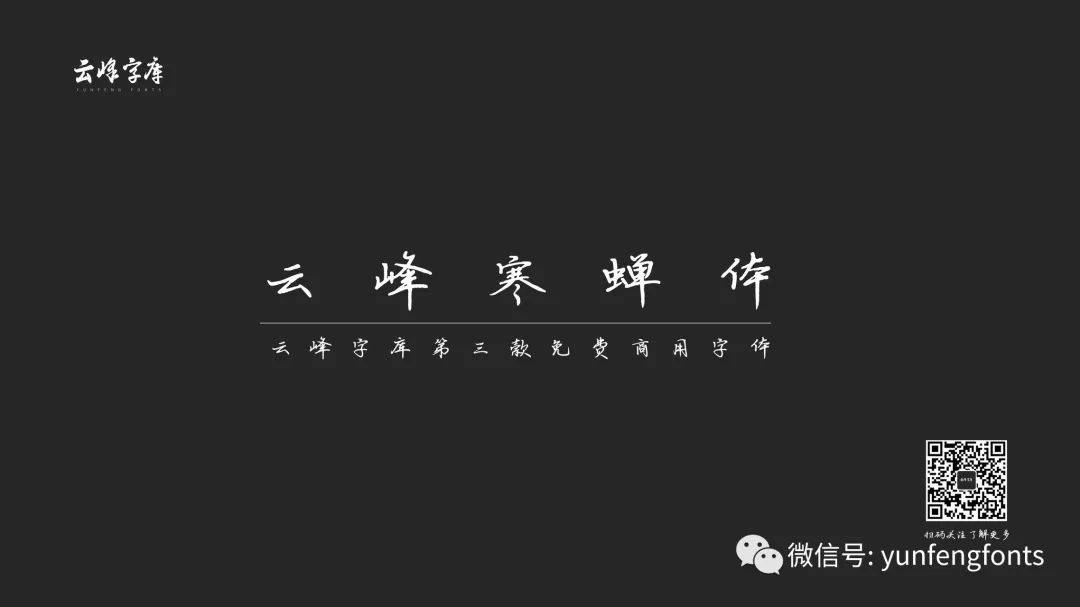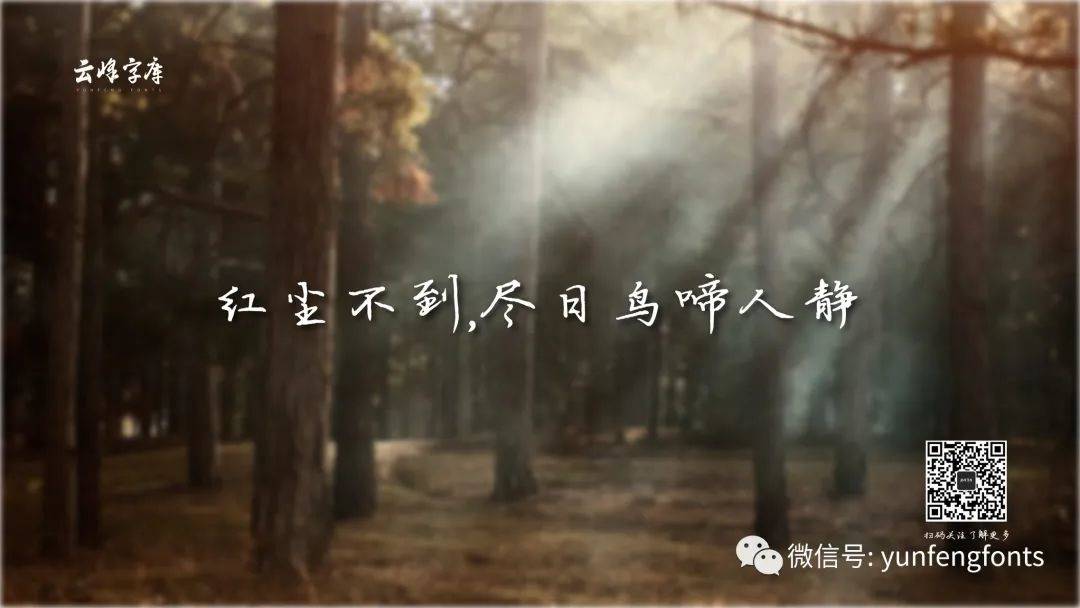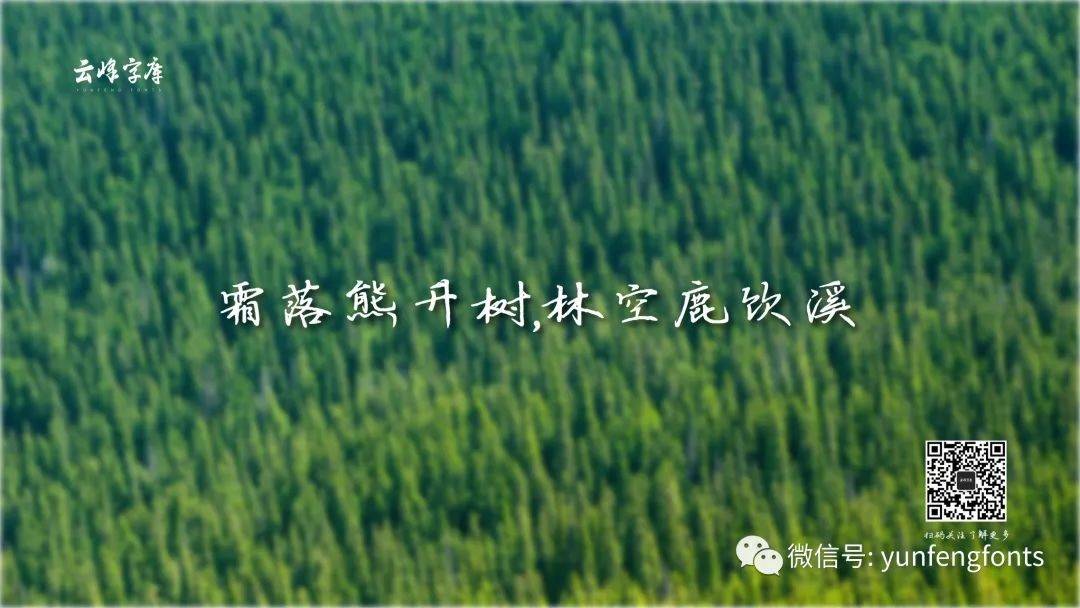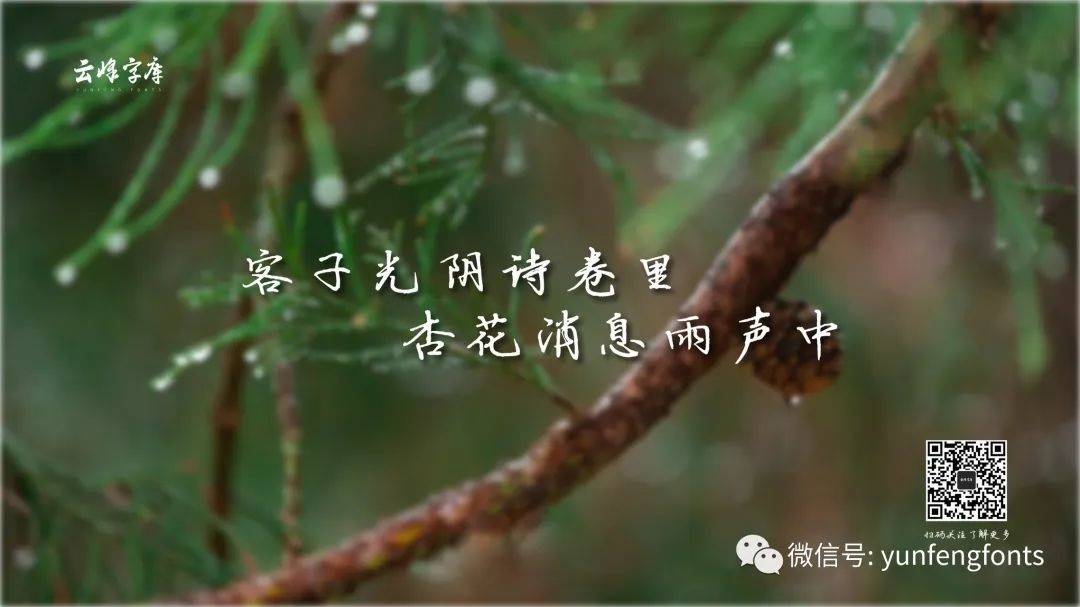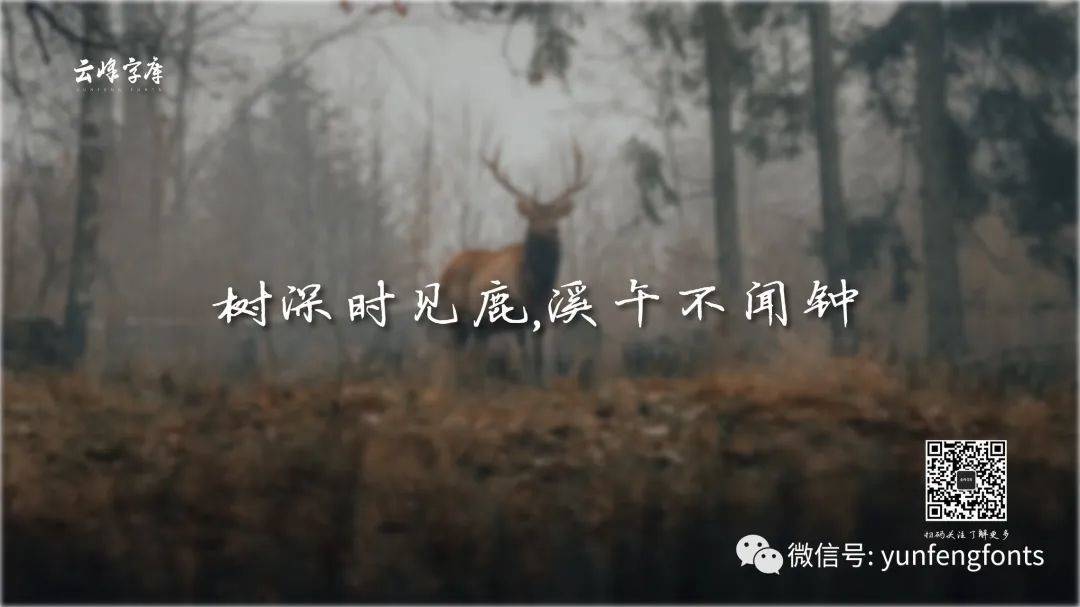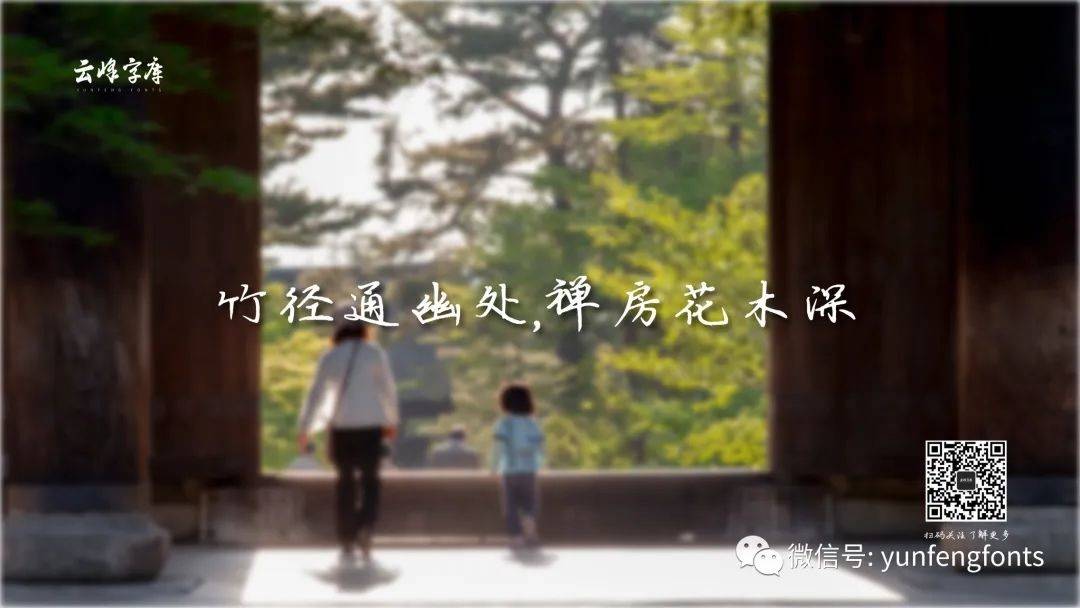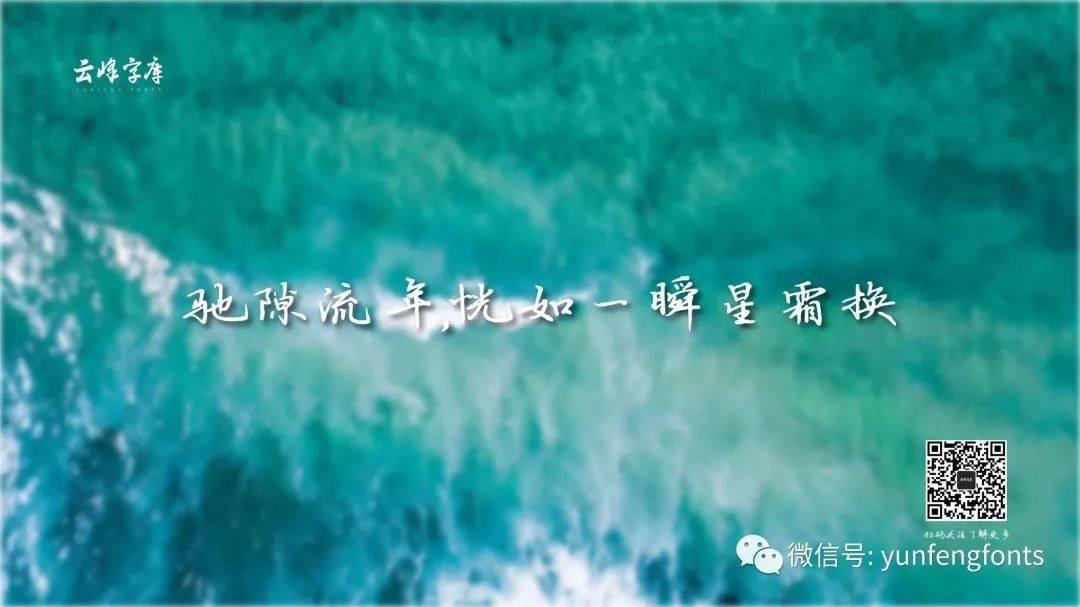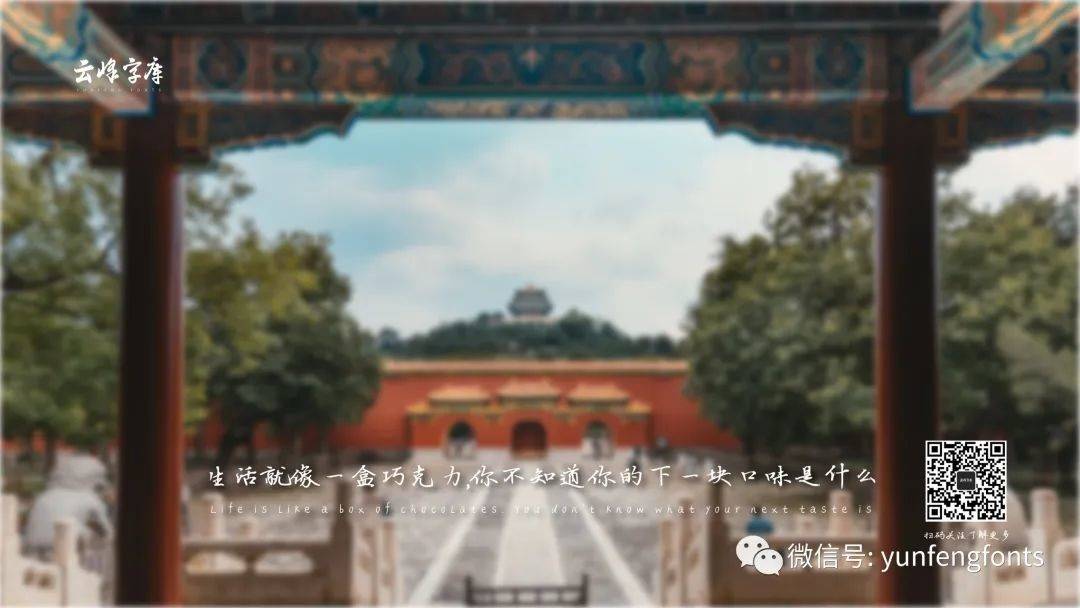
“云峰寒蝉体”是一款一位美丽少女书写的一款手写字体,这款字很漂亮、耐看,非常适合阅读、排版,可用于海报宣传、书籍排版、装订、文案排版、自媒体视频字幕等,整体阅读性强,是一款好看且实用的硬笔书法字体,欢迎大家使用。在使用过程中如有发现错别字及其它任何问题请反馈到QQ群205961668。
“云峰寒蝉体”是一款书写很新颖的字体,字体大方,适合各种设计作品使用!欢迎下载!